How typefaces are designed & fonts are made 字型設計與製作
Who makes typefaces? 誰在設計字型?
字型設計師是專業的字型創作人士。雖然字型制作軟體讓更多設計師能製作字型,但優質字型仍需大量時間和專業技能。
現代字型支援多種語言和排版功能,比20世紀的字型功能更強,但製作難度更大。
字型制作有通用方法,但質量差異大。業餘製作的字型往往不夠完整,而商業字型主要由專業字型公司製作。
How do new typefaces come into existence? 新字型是如何誕生的?
新字型的誕生有兩種方式:一是字型設計師憑藉靈感創作,可能是復興歷史字型,跟隨設計潮流,或填補市場空白;二是企業委託設計師定製專屬字型,打造獨特的品牌形象。
Why make more typefaces?為什麼還要設計新字型?
現力,還能透過不同的樣式(如加粗標題)來展示層次結構,幫助設計師更好地區分正文、註釋等不同內容。就像音樂一樣,每種字型都能傳達獨特的視覺感受。字型不僅能讓文字更有表
The importance of a brief 字型設計前的準備工作
在開始設計前,設計師需要明確以下要點,這些問題的答案會形成一個明確的字型設計方案:
- 字型的主要用途:是用於長篇閱讀還是標題展示?
- 特殊要求:是否需要考慮小字號清晰度、電子裝置顯示等具體場景?
- 語言支援:需要支援哪些國家的文字?是否需要特殊符號?
- 字重樣式:除了常規、斜體、粗體外,是否需要更多變體?
- 市場調研:與現有字型相比,新字型是否具有獨特優勢?
The Process 設計過程
雖然字型最終是數字檔案,但設計師往往先用手繪草圖來構思。他們會先畫出一些關鍵字母,這些字母能體現整套字型的基本特徵。透過這些字母,設計師可以探索如何讓整套字型看起來和諧統一。
設計師通常從設計幾個小寫字母開始,比如"n"和"o",因為這些字母能體現字型的基本特徵。接著設計大寫字母,通常從"H"和"O"開始,來確定字母的尺寸比例。字母之間要保持一致性,這樣讀者才容易閱讀。隨著設計的深入,可能需要調整已完成的字母,使整體更協調。
Drawing 字型繪製
完成草圖後,設計師會用專業軟體將手繪稿轉換成數字形式。軟體使用貝塞爾曲線來繪製字型,透過控制點來調整字形的形狀。常用的字型設計軟體包括FontLab、Glyphs和Robofont。
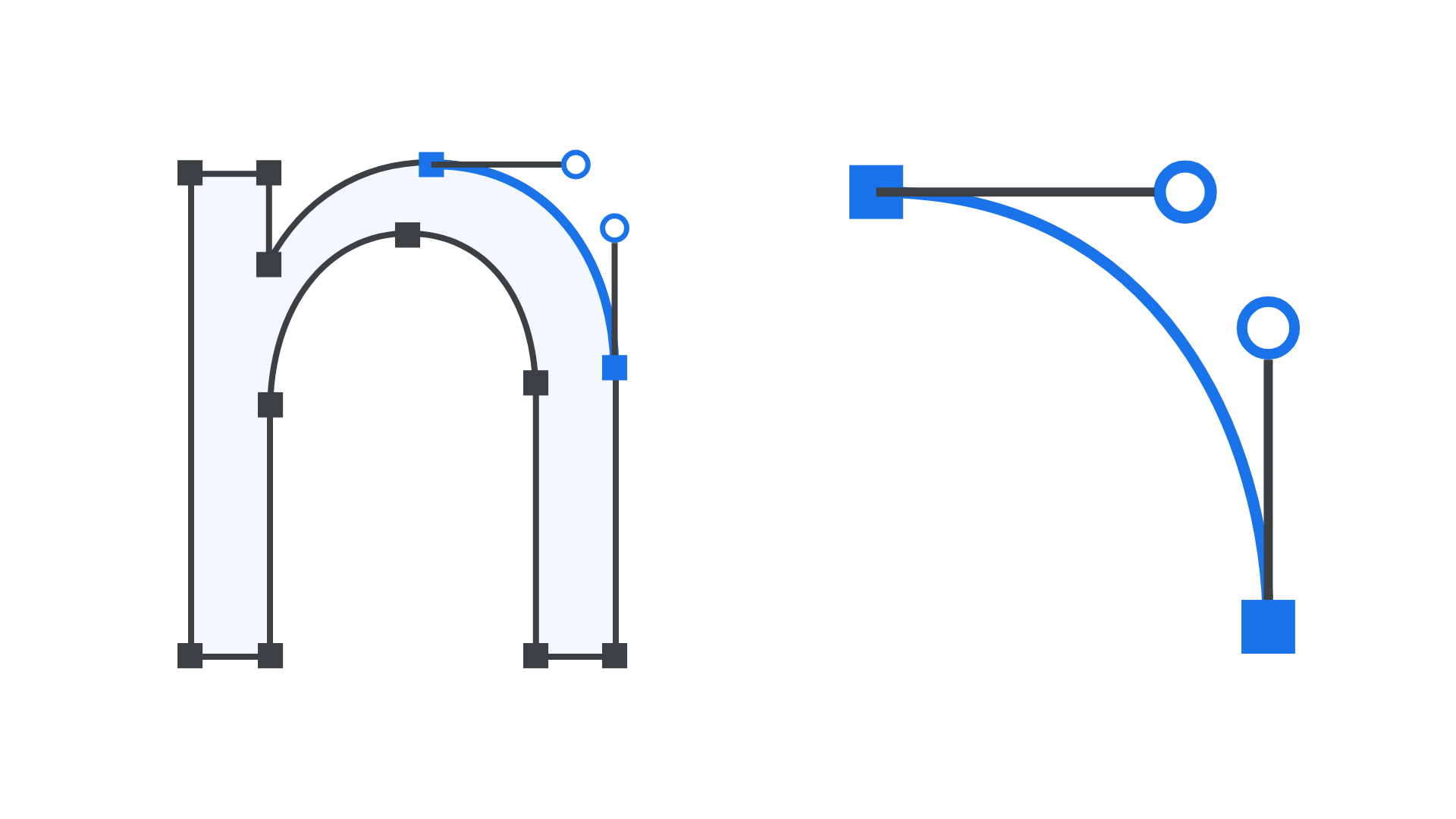
Spacing and Kerning 字距調整
設計師需要給每個字元設定合適的間距。有些字母組合(比如"VA")可能需要特別調整,這種調整叫做字偶距調整(kerning)。
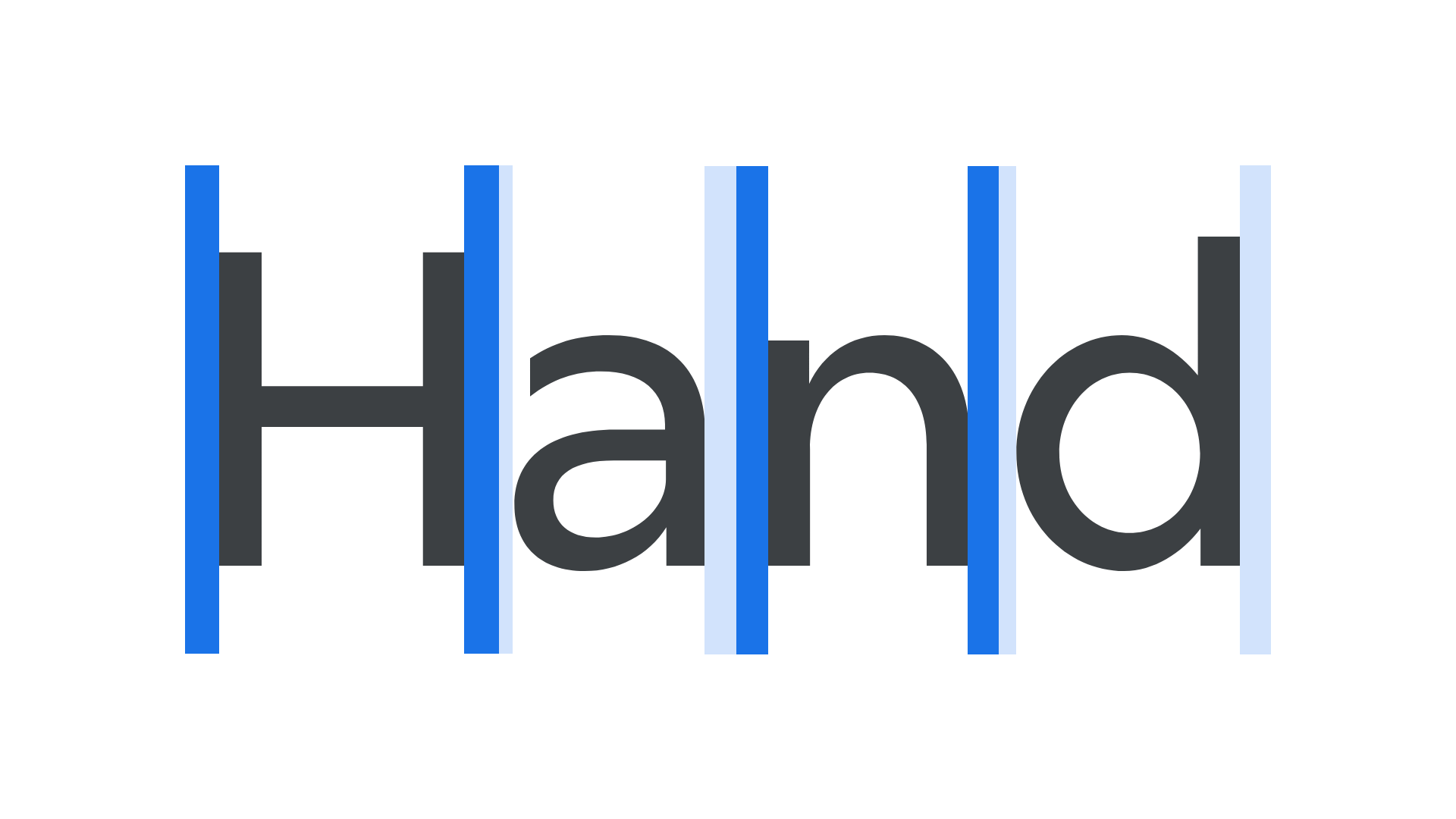
Masters 主要樣式
如果一個字型家族需要不同的粗細或寬度,設計師只需要設計最粗和最細的版本,中間的版本可以由軟體自動生成。這種極端版本稱為"masters"(主版本)。
Programming 程式設計
設計師可以用程式設計讓字型變得更智慧。比如說,透過OpenType這項技術,字型可以根據需要自動改變顯示方式。當你在寫不同的語言時,字型會自動使用合適的重音符號,你還可以手動選擇不同的字型樣式。
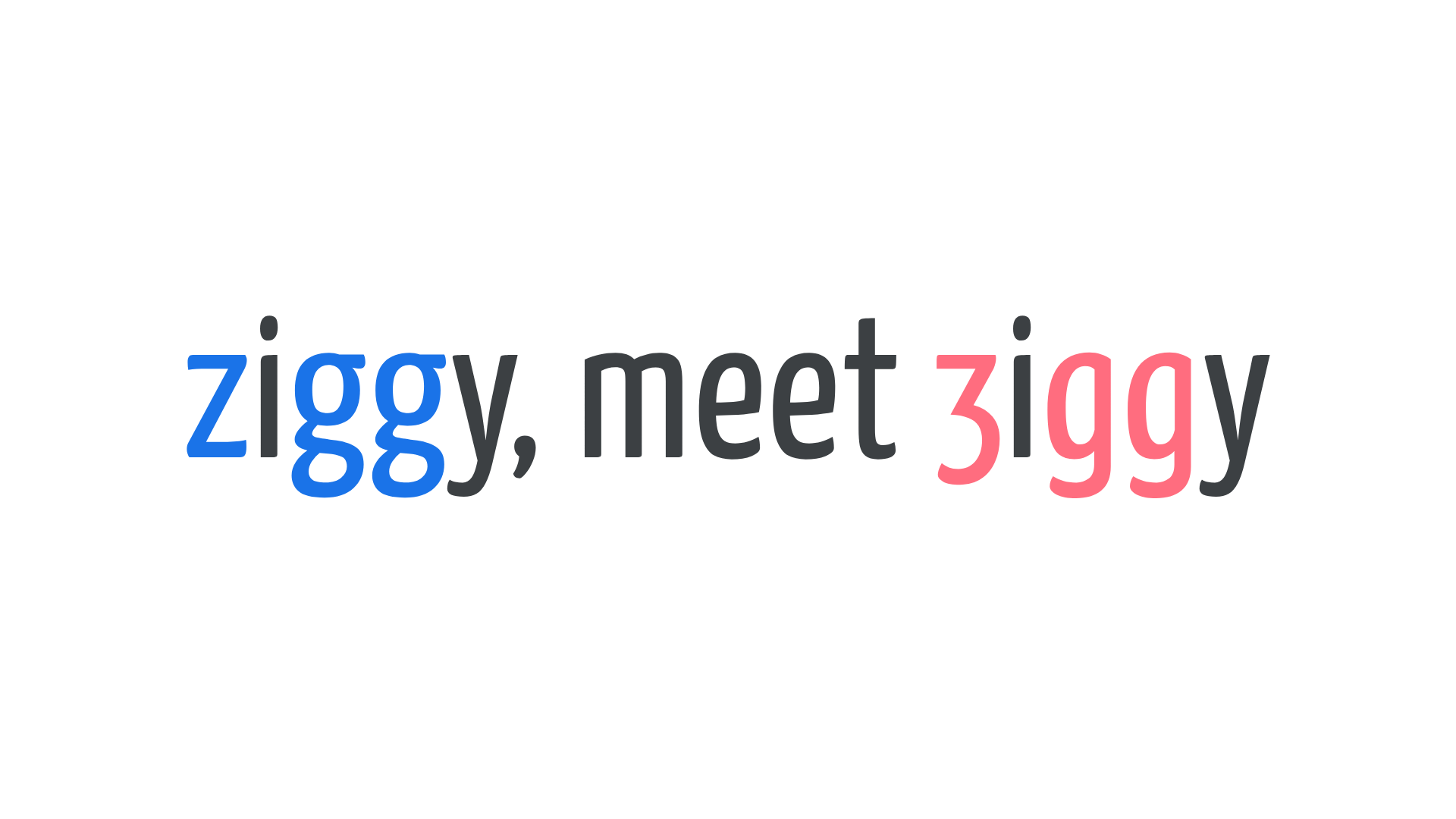
Mastering, Distribution, and Usage 製作完成與釋出使用
設計師會檢查和修正字型錯誤,然後匯出TTF或OTF格式檔案供使用。字型可透過設計師網站購買,也可訂閱或租用。字型使用受許可證約束,開源許可較自由,商業許可更嚴格。字型公司會製作樣本展示特點和用途進行營銷。